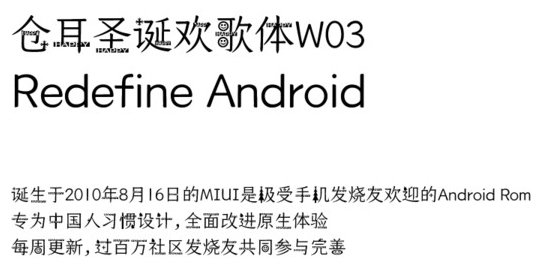
倉耳圣誕歡歌體是倉耳字庫官方推出的一款圣誕節(jié)氣息的卡通字體,多種點綴和修飾讓文字更加突出顯眼,給大家?guī)砼氖フQ的極佳體驗,喜歡的朋友就來綠色資源網(wǎng)免費體驗吧!
這是一款專為圣誕節(jié)定制的字體,在倉耳今楷結(jié)構(gòu)和筆形的基礎(chǔ)上,筆畫中增加了一些圣誕節(jié)的圖案元素,更加烘托出了節(jié)日氣氛。
倉耳字庫均有比較突出的藝術(shù)效果,而這款倉耳圣誕歡歌字體英文明亮而干爽,中文有著可愛的團和變形,給文字更加舒適的童真體驗,可以使用在藝術(shù)設(shè)計、平面設(shè)計等場合。